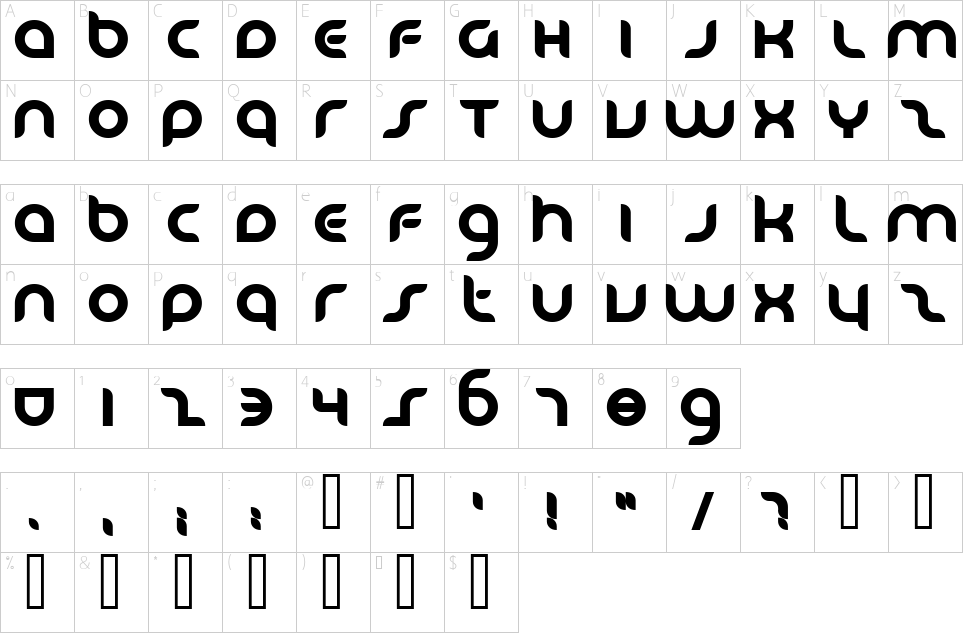
A fonte Danube oferece uma experiência gráfica agradável e envolvente, ideal para criar designs de alto nível. Desenvolvida pelo designer não informado, essa fonte é uma escolha perfeita para quem procura uma opção de tipo moderna e elegante. Com seu design cuidadosamente pensado, a fonte Danube é uma ótima escolha para qualquer projeto de design, desde identidades corporativas até designs gráficos em sites. Confortável de usar e com uma variedade de opções de tamanho e negrito, essa fonte é ideal tanto para profissionais quanto para iniciantes no design. Com sua vasta gama de usos, a fonte Danube é uma fonte gráfica gratuita que vale cada download. Eles não contam os downloads, pois são downloads para todos. Descubra e inclua a fonte Danube em seu próximo projeto.